4月10日,OPPO Reno系列新品发布会上,OPPO公布了全新的品牌Logo,并定制了一套全新字体 OPPO Sans,它针对移动端做了很多像素级的优化。
OPPO Sans新字体采用了全新骨架,中宫自然舒适,结构稳定,字形舒展,强化了屏幕显示的易读性和美观性。视觉重心的提高,让整体造型看起来挺拔优雅,充满生命力。此外,该字体简洁富有变化的线条融入OPPO产品曲线美学,更具现代感和未来感。
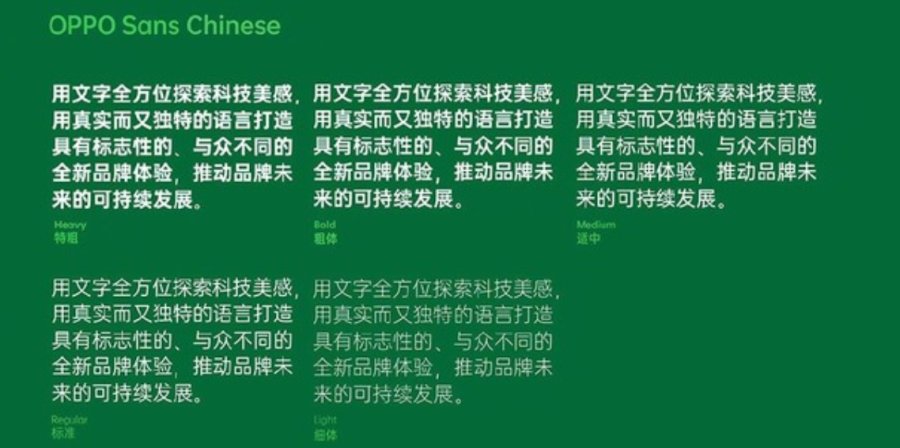
除了OPPO Sans新字体正式上线,阿里巴巴设计官方昨日在UCAN 2019 设计大会上,正式发布了一款字体“阿里巴巴普惠体”,官方称这是一款由中国企业首次发布的可面向全场景使用的免费商用正文字体。
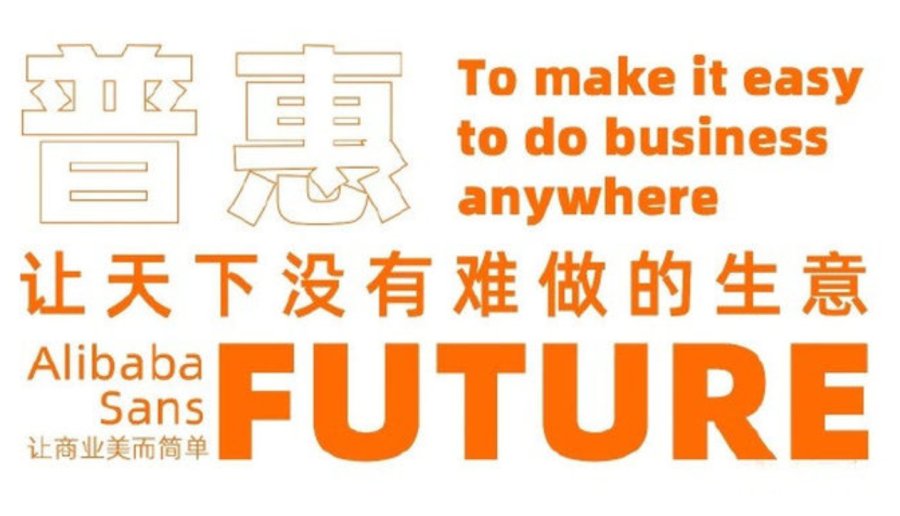
据介绍,中文字体多采用现代简洁的笔画,造型上偏瘦长,并将字的重心提高,字体笔画上也做了一些简化,如标题字省略出脚部分,更显简洁。